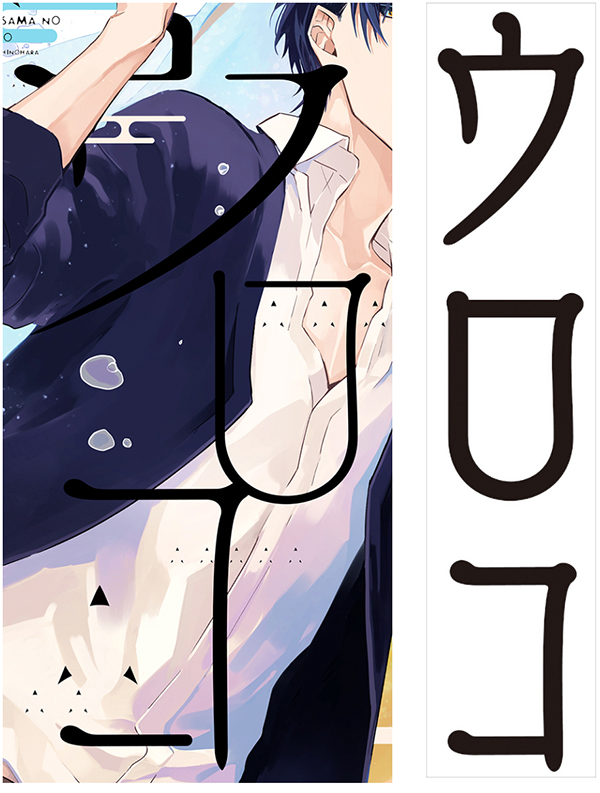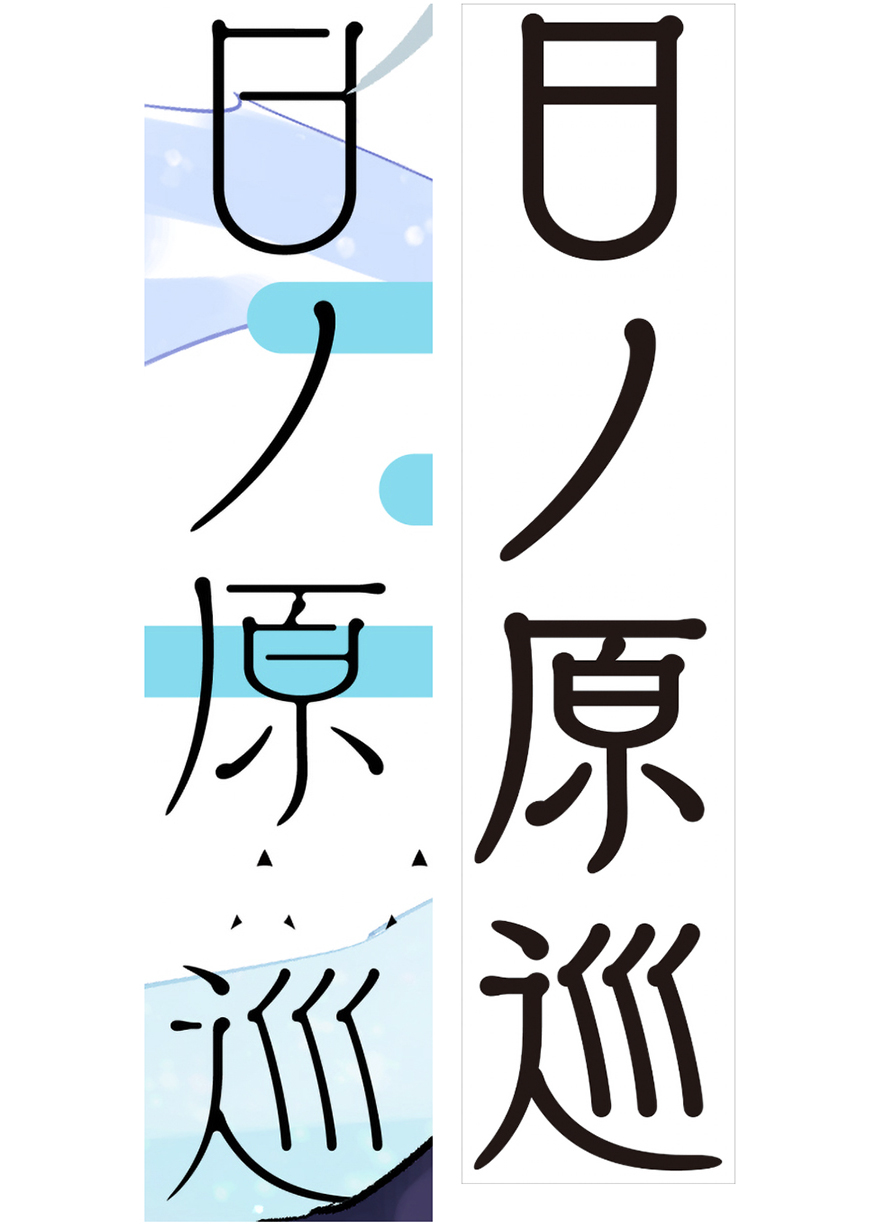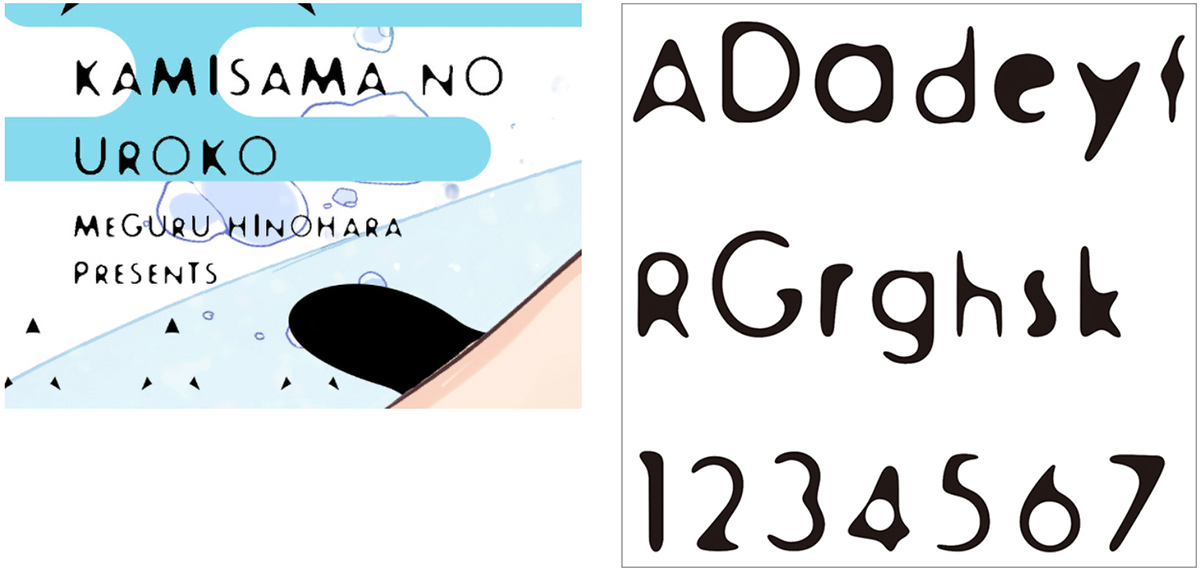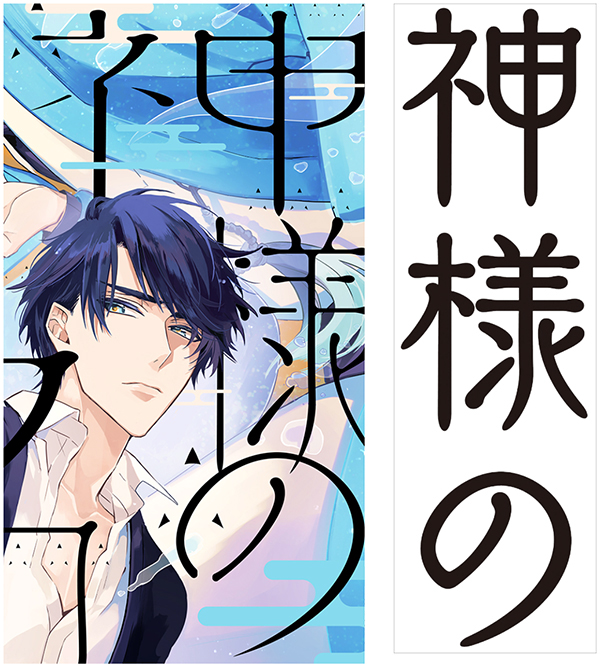
今回はコミックス『神様のウロコ 1/日ノ原巡』の使用フォントをご紹介。本記事はデザイン構成において重要な「フォント」の選定プロセスや加工方法を、貴重なプロの実例から紐解いてデザイン制作に役立てる連載です。
程よい軽さのある文字でクスッと笑える印象に
新作の執筆に行き詰まって田舎に帰った小説家の智治と、彼が故郷で出会った美形の龍神の恋愛模様を描いたBLコミックス『神様のウロコ 1/日ノ原巡』の表紙カバー。現代の世の中に和服姿の龍神が登場するという作品の神秘的な世界観が、端麗なメインイラストや抽象的な雲の意匠、龍の爪をイメージしたパターン、レトロ感を強調したタイトル文字などで印象的に表現されている。
Font.01「ライラ DB」
篆書体風の文字を加工してレトロ感を強調
メインタイトルの文字は、竪琴を連想させる優しく不思議な雰囲気の書体「ライラ DB」(フォントワークス)がベースに。その重心が高く縦に長い篆書体風のデザインが、龍神と人の恋愛を描いた作品の神秘的でレトロな雰囲気に適しているため選択された。
レトロ感をより強めるため、ステンシル風の加工やエッジのラウンド加工、墨だまりのようなにじんだ感じの加工が施されている。また、長体をかけた文字と平体をかけた文字を混在させることで、水面に映った文字の揺らめきをイメージさせるという技ありの工夫も。
Font.02「ライラ DB」
タイトルロゴに合わせたデザイン書体で統一感を
作者名「日ノ原巡」部分の文字は、作品の世界観を意識してタイトルロゴと同じ「ライラ DB」(フォントワークス)が選択された。全体のバランスを考慮して、文字を細めたり、ステンシル風に加工するなどして使用されている。
Font.03「Fur Light」
全体の雰囲気を考慮してにじんだ風合いの文字に
タイトルの欧文表記「KAMISAMA NO UROKO」の文字は、ペンで手書きしたような遊びのある風合いが特徴的な書体「Fur Light」(T-26)をチョイス。インクがにじんだような文字が、作品の世界観やタイトルロゴの方向性と相性がよいため選択された。